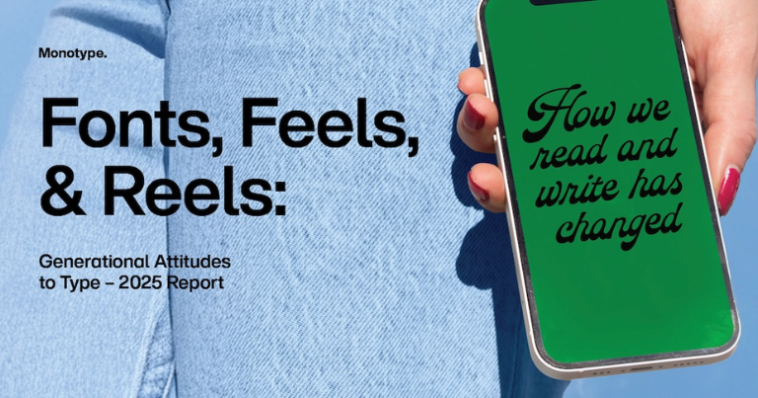
Monotype-ის ახალი კვლევა კიდევ ერთხელ ადასტურებს, რომ ტიპოგრაფია თვითგამოხატვის საშუალებაა. თავისივე Fonts, Feels, & Reels-ის ახალი მოხსენების ფარგლებში 12 000 მომხმარებელი შეისწავლა 6 ქვეყანაში და პასუხი გასცა კითხვას: როგორ უყურებენ Z თაობა, მილენიალები, X თაობა და ბუმერები შრიფტებს სამყაროში, რომელშიც ყველა პოსტი პირველი შთაბეჭდილების მოხდენის საშუალებად ითვლება? აი, პასუხებიც:
1. ფონტები ფონური ხმაური კი არა, ციფრული ხმაა
დღეს შრიფტები ისეთივე წონას ატარებს, როგორსაც თავის დროზე ხელნაწერები. კვლევის თანახმად, გამოკითხულთა 69% სოციალური მედია პოსტების შედგენისას ფონტებს უმნიშვნელოვანეს ნაწილად თვლის, მათგან თაობა ზეტისა და მილენიალების წარმომადგენლებმა კი უფრო მეტი იციან შრიფტების შესახებ, მათ შორის ისიც, თუ როგორ აირჩიონ სანდოობისა და პერსონალიზმის გათვალისწინებით.
2. შრიფტები ემოციებს გადმოგვცემს
ჩათვალეთ, რომ შრიფტი ტანსაცმელია, რომელსაც თქვენსავე სიტყვებს აცმევთ. თაობა ზეტის 65% და მილენიალების 67% ამბობს, რომ მათი შერჩეული ფონტი პირდაპირ მათ ტონს განაპირობებს. გამოკითხულთა 60% კი მიიჩნევს, რომ ტიპოგრაფია პერსონალიზმის გამოხატვაში მნიშვნელოვან როლს ასრულებს, როცა 65% მის დამხმარე როლზე საუბრობს მნიშვნელობის გადმოცემაში. რაც შეეხება ახალგაზრდებს, მათთვის ფონტები უბრალო დეკორაცია კი არა, ემოციების გამომხატველი რამ არის, რაც მანამ აყალიბებს განწყობას, სანამ სიტყვას წაიკითხავენ.
3. კარგი ფონტი = კარგი ჩართულობა
რესპონდენტების 78% თანხმდება, რომ გამორჩეული და კარგად შერჩეული ფონტები მოწონების, გაზიარებისა და კომენტარის რაოდენობას ზრდის. თაობა ზეტის 87%-იც ამას ეთანხმება… აქედან გამომდინარე კი შეგვიძლია ვთქვათ, რომ შრიფტები აუდიტორიაზე მანამ ზემოქმედებს, სანამ მოწონების ღილაკზე თითის დაჭერას გადაწყვეტენ.
4. ფონტების სიმწირე სოციალურ ქსელებში რეალური პრობლემაა
ინსტაგრამის შეზღუდულმა არჩევანმა თუ დაგღალათ, თქვენც ამ ადამიანთა რიცხვს მიეკუთვნებით. კვლევის თანახმად, თაობა ზეტისა და მილენიალების ნახევარი წუხს იმის გამო, რომ სოციალურ მედია პლატფორმებზე ფონტების დაბალი არჩევანია. ამიტომაც უმეტესობა პოსტების დიზაინს პლატფორმის მიღმა აკეთებს და ისეთ პლატფორმებს მიმართავს, როგორებიცაა Canva, Figma და Adobe Express. ეს დამატებითი ძალისხმევა პოსტების განთავსების პროცესს აფერხებს, მეორე მხრივ კი, გვაჩვენებს, რამდენად ადარდებთ ახალგაზრდა კრეატორებს, რომ პლატფორმაზე სწორად გამოიყურებოდნენ.
5. შრიფტი პირველ შთაბეჭდილებას ქმნის
ამასობაში, ტიპოგრაფიამ სოციალურ სივრცეში ისეთივე წონა შეიძინა, რაც ფიზიკურ სივრცეში ხელის ჩამორთმევამ… თაობა ზეტის დაახლოებით 70% და მილენიალების 66% ამბობს, რომ შერჩეული შრიფტი მათ შთაბეჭდილებაზე ზემოქმედებს. გამოკითხულთა ნახევარზე მეტი კი მიიჩნევს, რომ ეს ზემოქმედებს ბრენდის ავთენტურობისა და სანდოობის აღქმაზე.
რა დატვირთვა აქვს შრიფტს განსხვავებული თაობების წარმომადგენლებისთვის?
- ბუმერების თაობა იმპულსურად აზიარებს კონტენტს, რაც იმას ნიშნავს, რომ ხშირად პოსტავენ, მაგრამ ფონტებს ძალიან დიდ მნიშვნელობას არ ანიჭებენ. ისინი ფოკუსირებულნი არიან თავად შეტყობინებაზე და არა, ესთეტიკაზე.
- X თაობის წარმომადგენლებს ნაკლებად ანაღვლებს ფონტების არჩევანის სიმწირე, მათთვის უფრო მნიშვნელოვანია შრიფტის გავლენა სანდოობაზე.
- მილენიალებს ექსპერიმენტები უყვართ, ისინი შრიფტს იდენტობის მთავარ ნაწილად აღიქვამენ, რომელიც შემოქმედებითობის ნოსტალგიებთან შერწყმის საშუალებას გვთავაზობს.
- თაობა ზეტის წარმომადგენლები კი სულით კრეატორები არიან — მათთვის ფონტები სოციალური ვალუტაა, ამიტომაც სხვების შერჩეულ შრიფტებსაც, საკუთარზე მწვავედ, განსჯიან.
Fonts, Feels, & Reels-ის მოხსენების ზოგადი შედეგები კი აი, ასეთია:
- ინფლუენსერებისა და კრეატორებისთვის ფონტები მათივე ვიზუალური ხმაა. საერთაშორისო არჩევანი კი სანდოობას განაპირობებს, ჩართულობას ზრდის და პოსტებს პერსონალური ბრენდის განაცხადებად აქცევს.
- ბრენდებისთვის ტიპოგრაფია ბრენდის მთავარი აქტივია და არა, დამამთავრებელი შტრიხი — ფონტი განაპირობებს სანდოობას, ავთენტურობასა და ცნობადობას დემოგრაფიებს შორის.
- ციფრული პლატფორმებისთვის ფონტების ბიბლიოთეკის გაფართოება მოგებიანი სვლა უნდა იყოს. ხომ გახსოვთ, თაობა ზეტისა და მილენიალების წარმომადგენლებს პერსონალიზაცია სურთ, შესაბამისად, უნდათ, აღნიშნული პლატფორმებმა დააკმაყოფილოს.